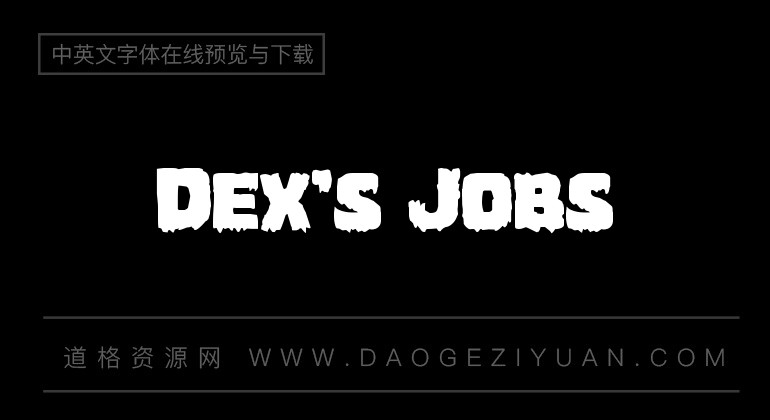
Dex's Jobs
? Dex's Jobs 是一款可爱的英文字体,由 Dexsar Harry Anugerah 创作。它具有独特的外观,以及简单的英文字母,使其成为一款十分实用的字体。它具有清晰的线条,细节丰富,使用它可以创造出精致而又有趣的文字。它也可以与其他字体搭配使用,以创造出更加精致的文字效果。
Dex's Jobs是一款非常不错的手写艺术字体,具有很好的视觉感,适合于文化类的宣传设计、商业类品牌的广告和产品包装设计以及个性化文字排版等较多场景。